상업용 무료 폰트 추천
상업용으로 사용이 가능한 무료 폰트 다섯가지 추천해드리고자 합니다. 마음에 드는 폰트 글꼴이 있으시면 다운받아 사용해 보시기 바랍니다.
1. G마켓 산스체 폰트
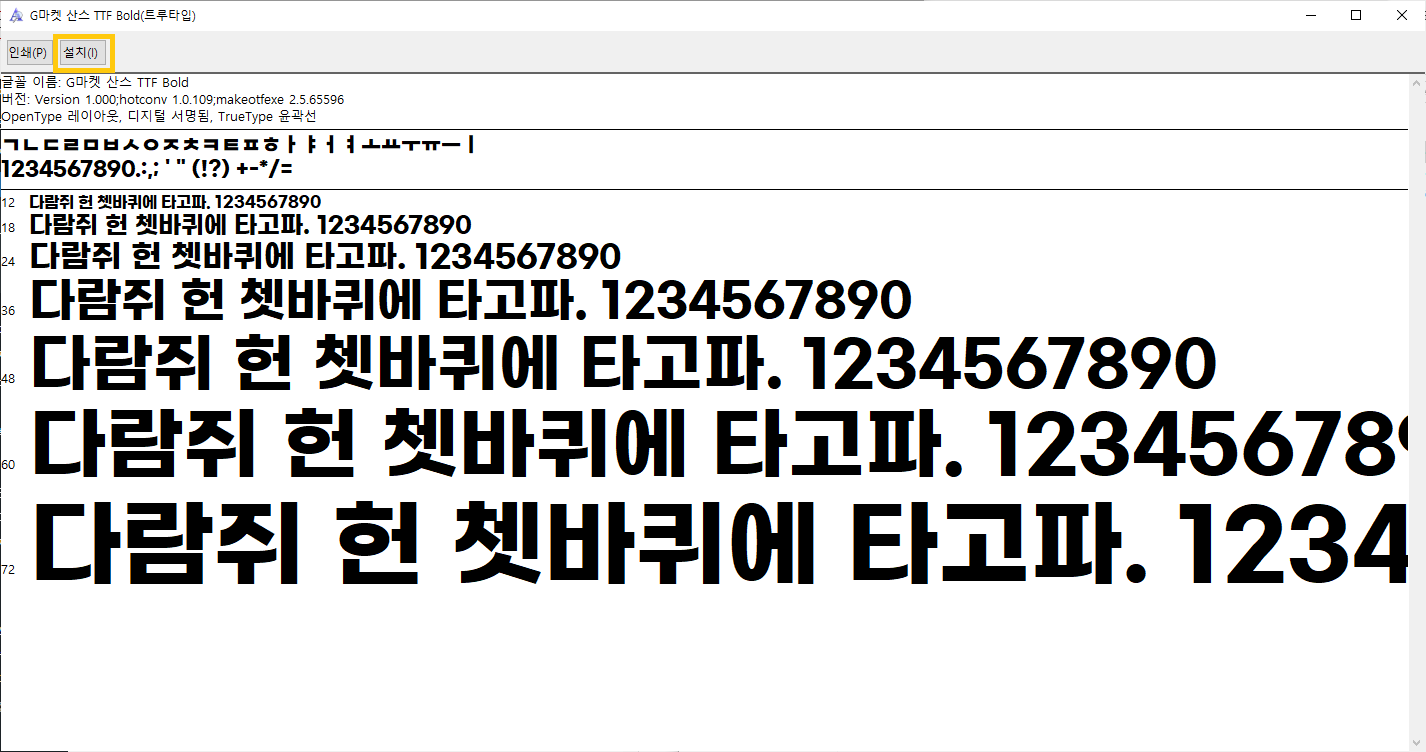
G마켓 산스체 폰트는 온라인 쇼핑몰 플랫폼인 G마켓(지마켓)에서 제공하는 브랜드 폰트입니다. 깔끔한 느낌이 나는 글꼴이며 G마켓에서는 ‘손으로 쓰는 자연스러운 필순을 그대로 따르기 때문에 친근하고 자연스러운 인상을 가지고 있습니다’ 라고 이야기해 주고있습니다. 부드러우면서 현대적인 느낌을 주는 것 같습니다.
2. 써라운드 에어체 폰트
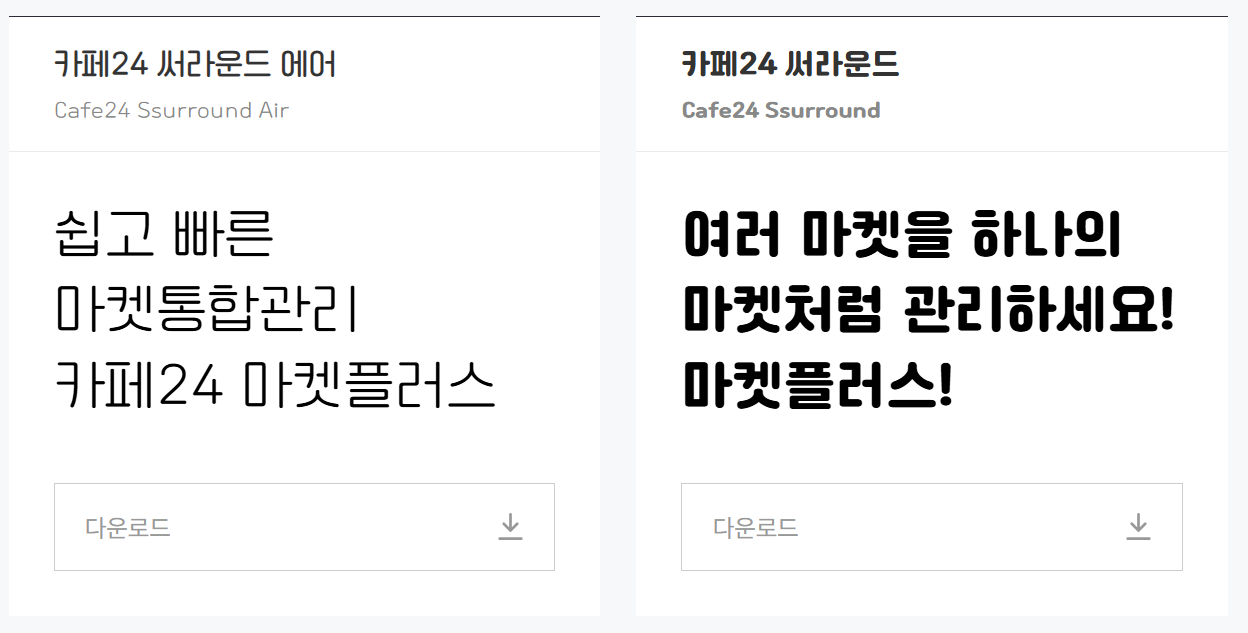
써라운드 에어체 폰트는 카페24(Cafe24)에서 개발한 상업용 무료 폰트 입니다. 카페24 써라운드 에어체와 써라운드체가 있습니다. 써라운드 에어체 폰트는 얇은 글씨체 이고 써라운드체 폰트는 굵은 글씨체로 되어있습니다. 굴림체의 조금 더 세련된 느낌의 글씨체이며 시옷을 사용할 때 쌍시옷의 서체가 매력적인 것이 특징입니다.
3. 런드리 고딕체 폰트
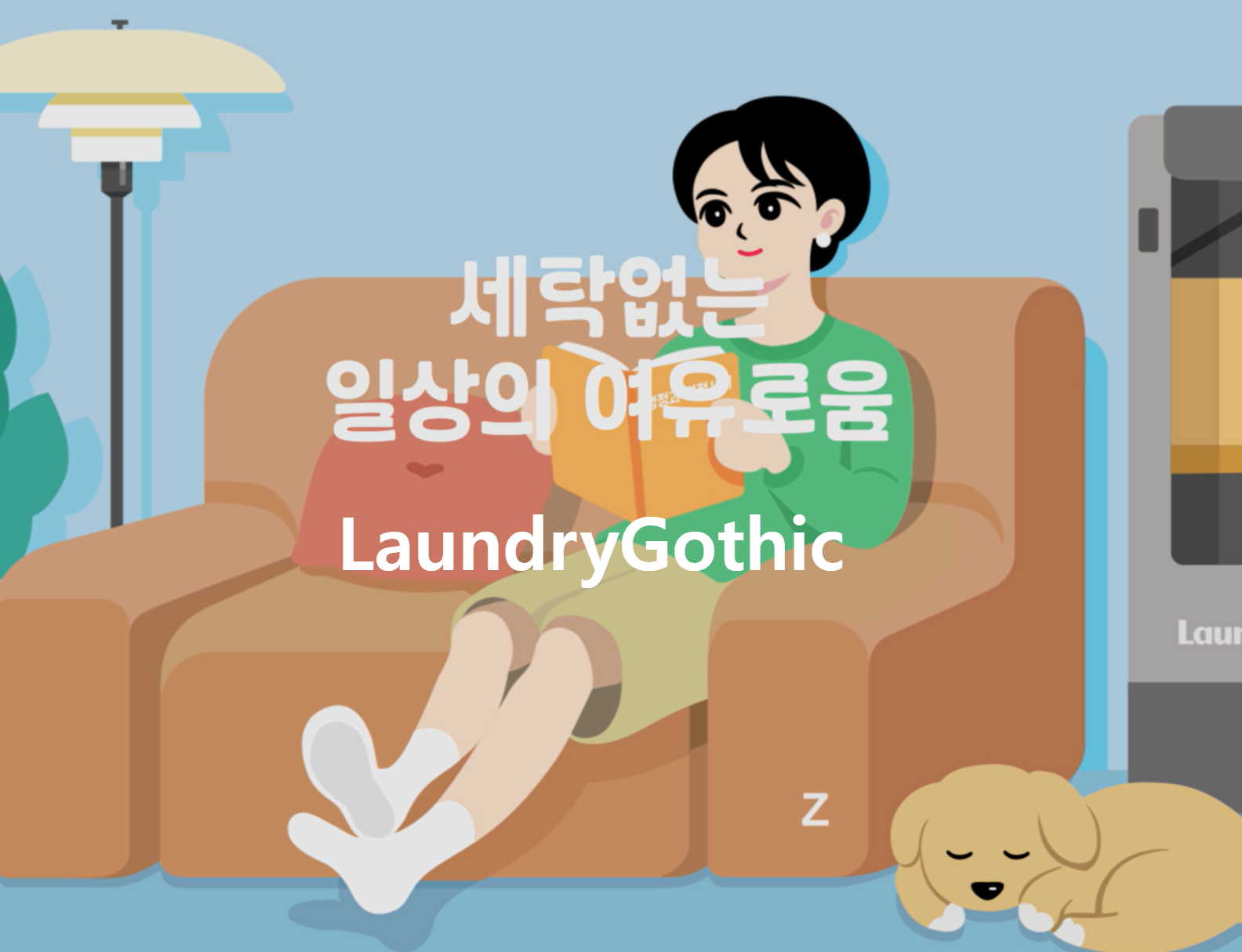
런드리 고딕체 폰트는 의식주컴퍼니에서 개발한 폰트입니다. 런드리 고딕체 폰트는 동글동글한 글씨체여서 딱딱 끊어지는 느낌이 아니기 때문에 친밀감을 줄 수 있는 글씨체입니다.
의식주컴퍼니에서 런드리 고딕체 폰트를 차곡차곡 개어진 세탁물을 닮은 새로운 서체라고 설명을 합니다. 그리고 세탁과정의 상쾌함을 담은 생동감 있는 획이 특징이라고 이야기해주고 있습니다.
4. 샌드박스 어그로체 폰트
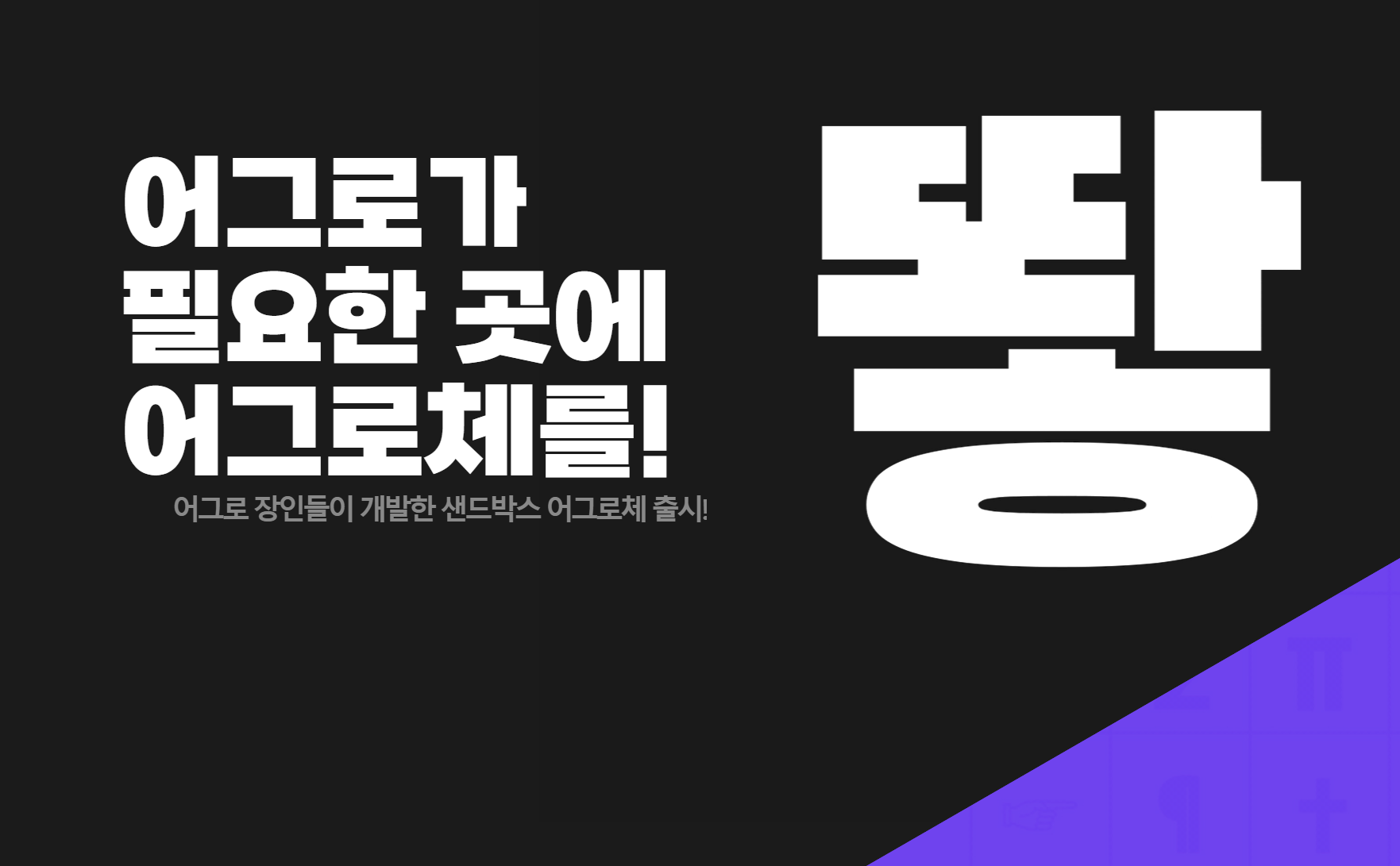
샌드박스 어그로체 폰트는 샌드박스 네트워크 회사에서 개발한 폰트입니다. 샌드박스 어그로체는 어그로가 필요할 때 써달라고 하는데요, 너무 귀엽지 않나요?
독특한 느낌이 나는 폰트로 모음 안쪽 획을 아래방향으로 꺾여져 있는 것이 큰 특징인 듯합니다. 샌드박스에서 이야기하는 어그로체만의 매력은 독특한 곡선과 사선의 조합과 높이와 폭에서 특유의 리듬감을 느낄 수 있게 만든 것이 특징이라고 이야기 해주고 있습니다.
저는 샌드박스 어그로체 폰트를 사용할 때는 재밌는 느낌이 나고 싶은 제목을 사용할 때 사용을 합니다.
5. 여기어때체 폰트
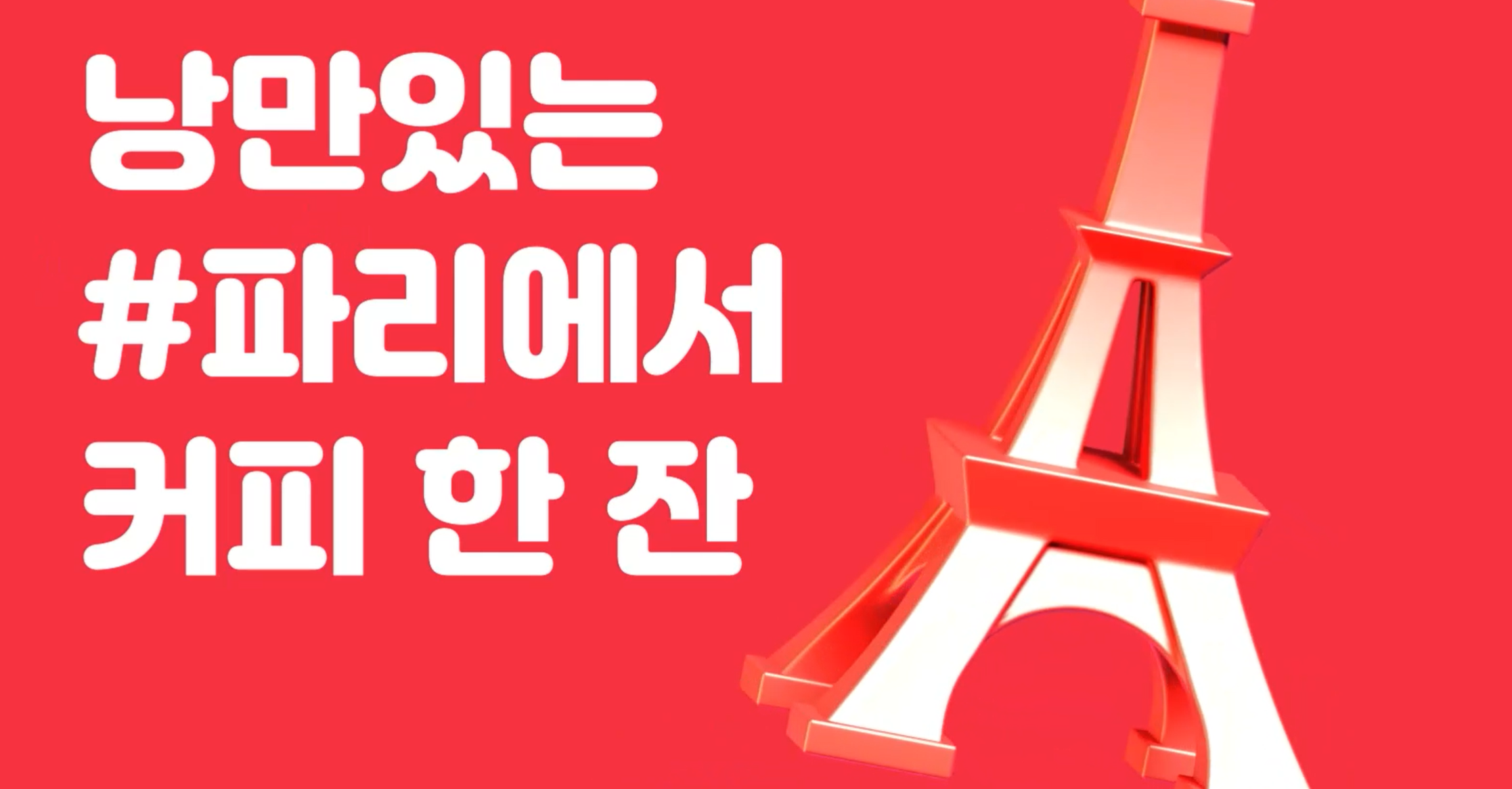
여기어때체 폰트는 여기어때 브랜드의 정체성을 담아 개발한 글꼴입니다. 글자의 곡선과 직선의 조합이 잘 어우러지게 되어있습니다. 윗쪽은 둥글고 아랫쪽은 직선으로 되어있는 것이 글꼴의 특징입니다. 제목으로 사용하기 좋은 폰트입니다.